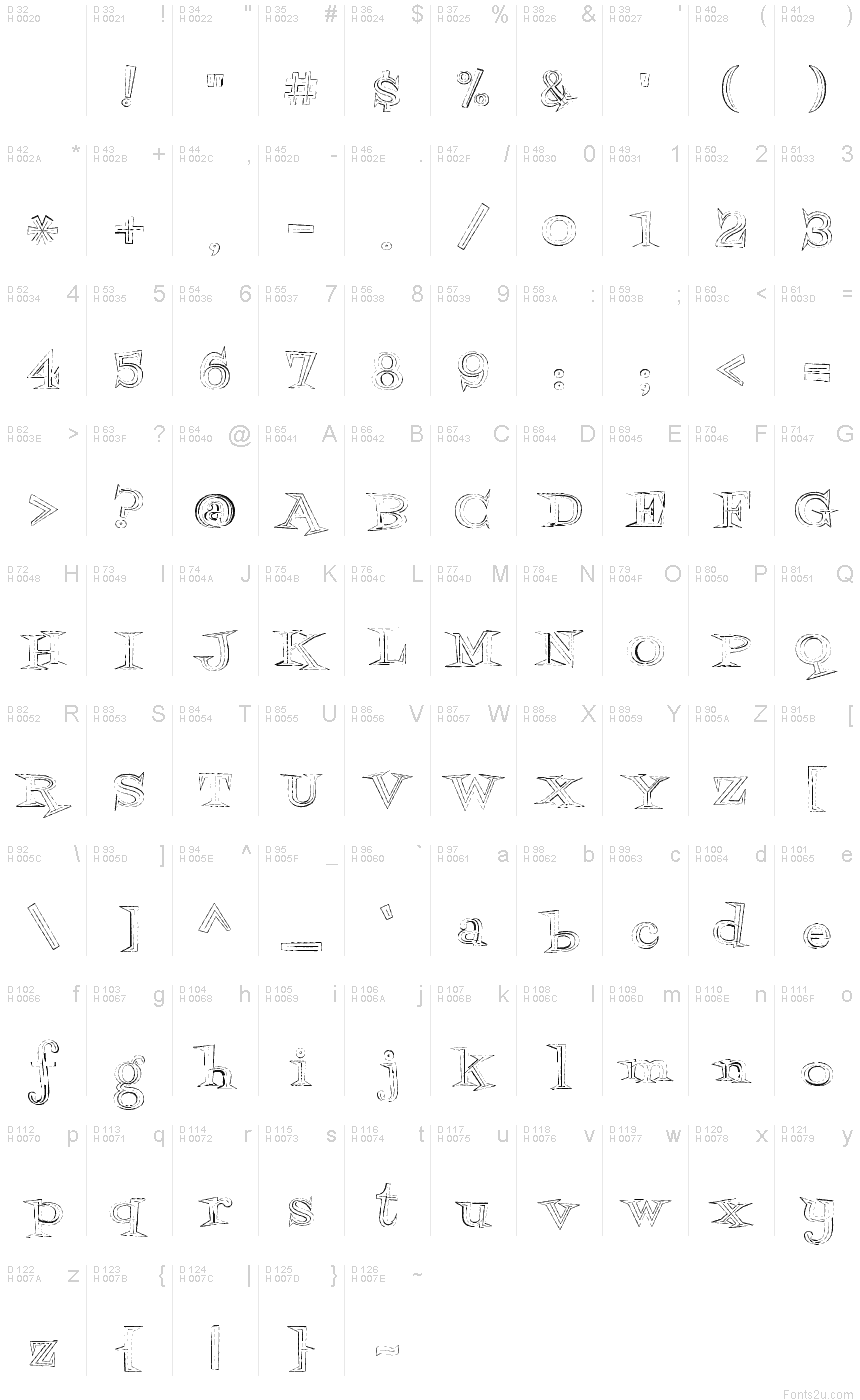
Fontdinerdotcom Jazz Light od Font Diner je bezplatné obrysové jazzové titulkové písmo s uvolněnou retro atmosférou klubové scény. Písmena kombinují vysoké, zužující se tahy s měkkými křivkami a ručně kresleným obrysem, který písmu dodává pružný, lehce improvizační rytmus, nikoliv jen strnulou vintage stylizaci.
Skvěle funguje na titulcích plakátů, koktejlových menu, obalech alb, festivalové grafice a titulních kartách, kde toto bezplatné písmo dokáže podtrhnout energii nočního života poloviny století a starých světelných nápisů. Protože obrys zůstává otevřený a tvary mají jemný divadelní švih, hodí se také pro krátké nadpisy, loga a iniciály, které vyžadují trochu toho „swingu“, aniž by sklouzly ke karikatuře.